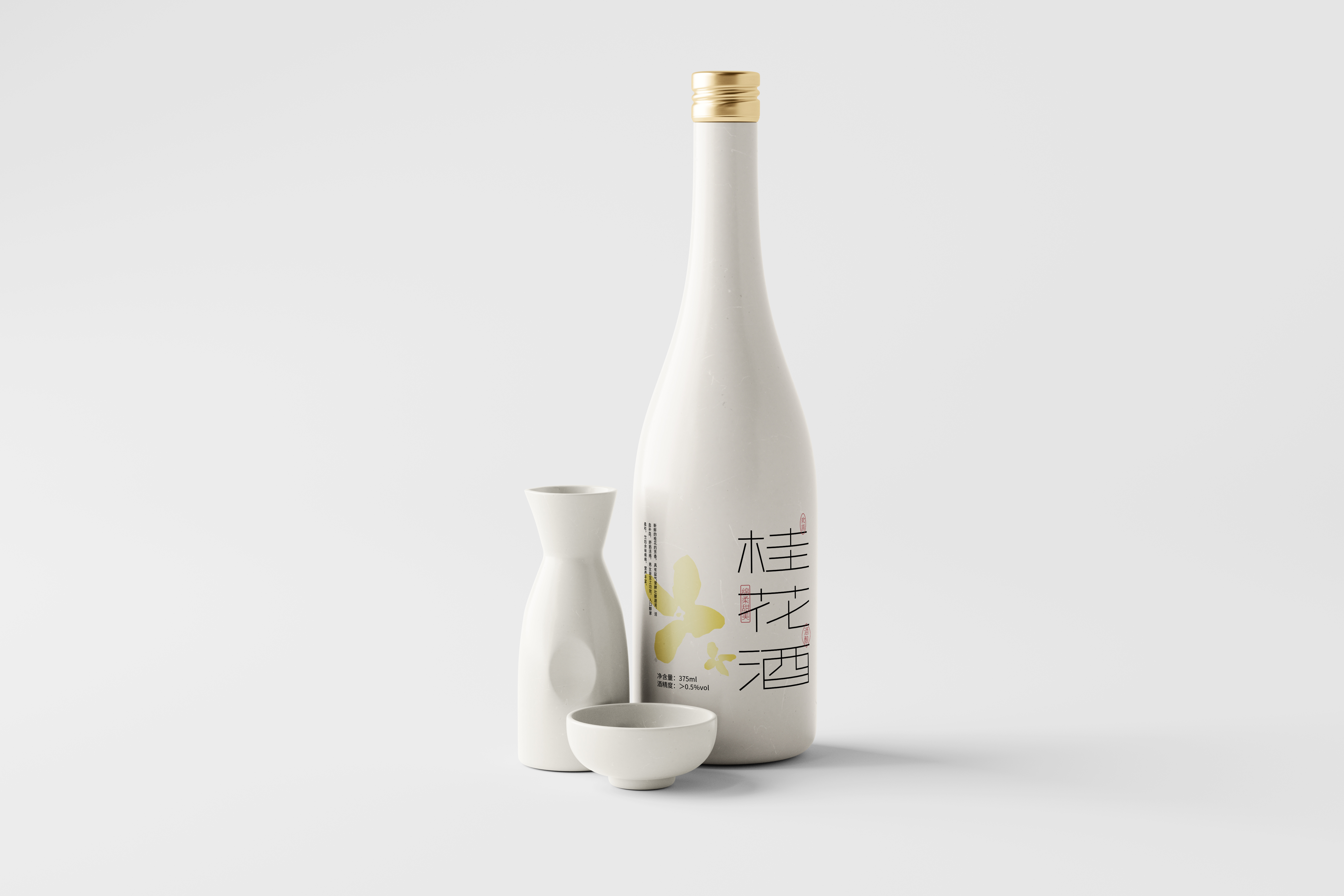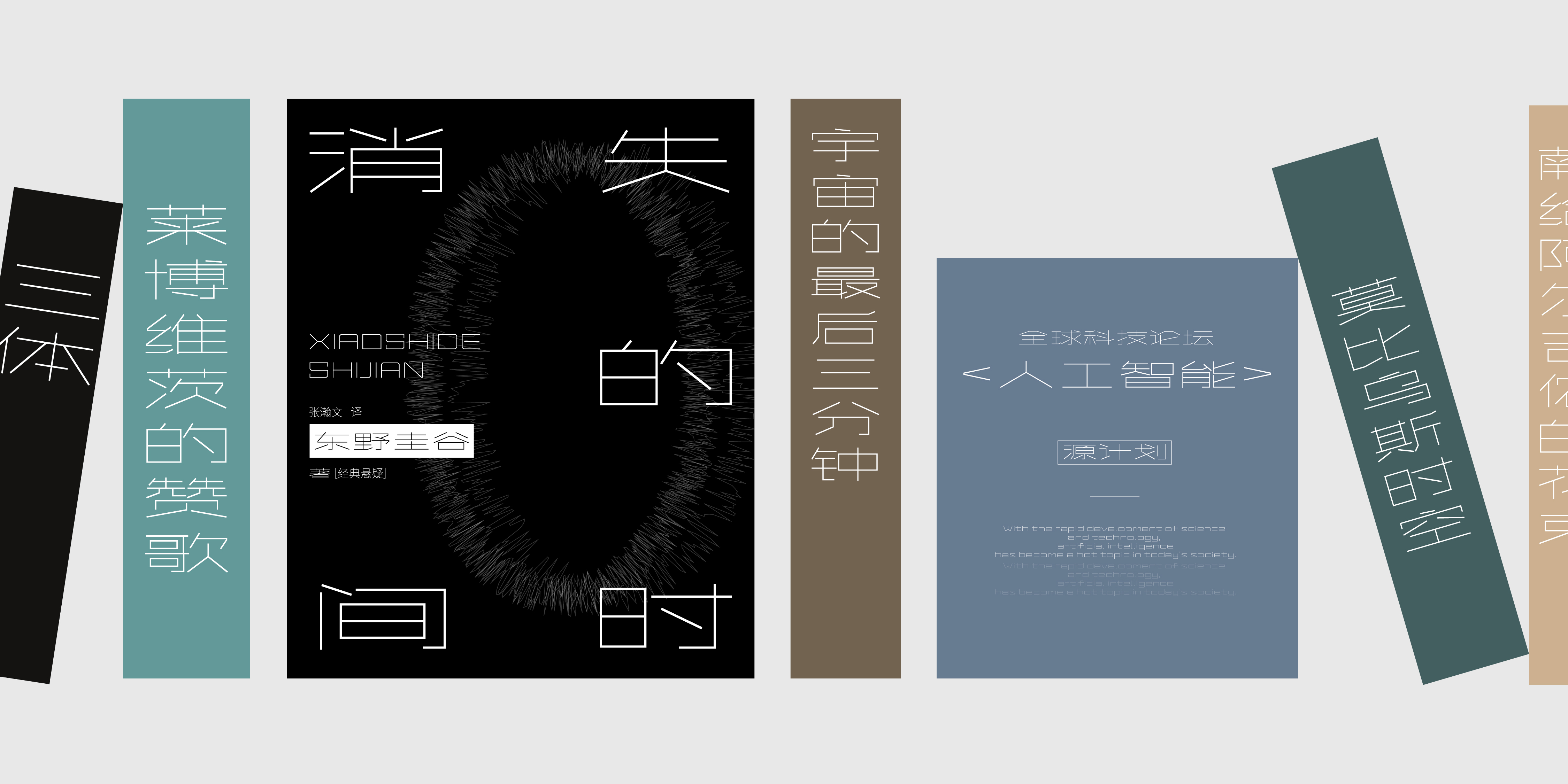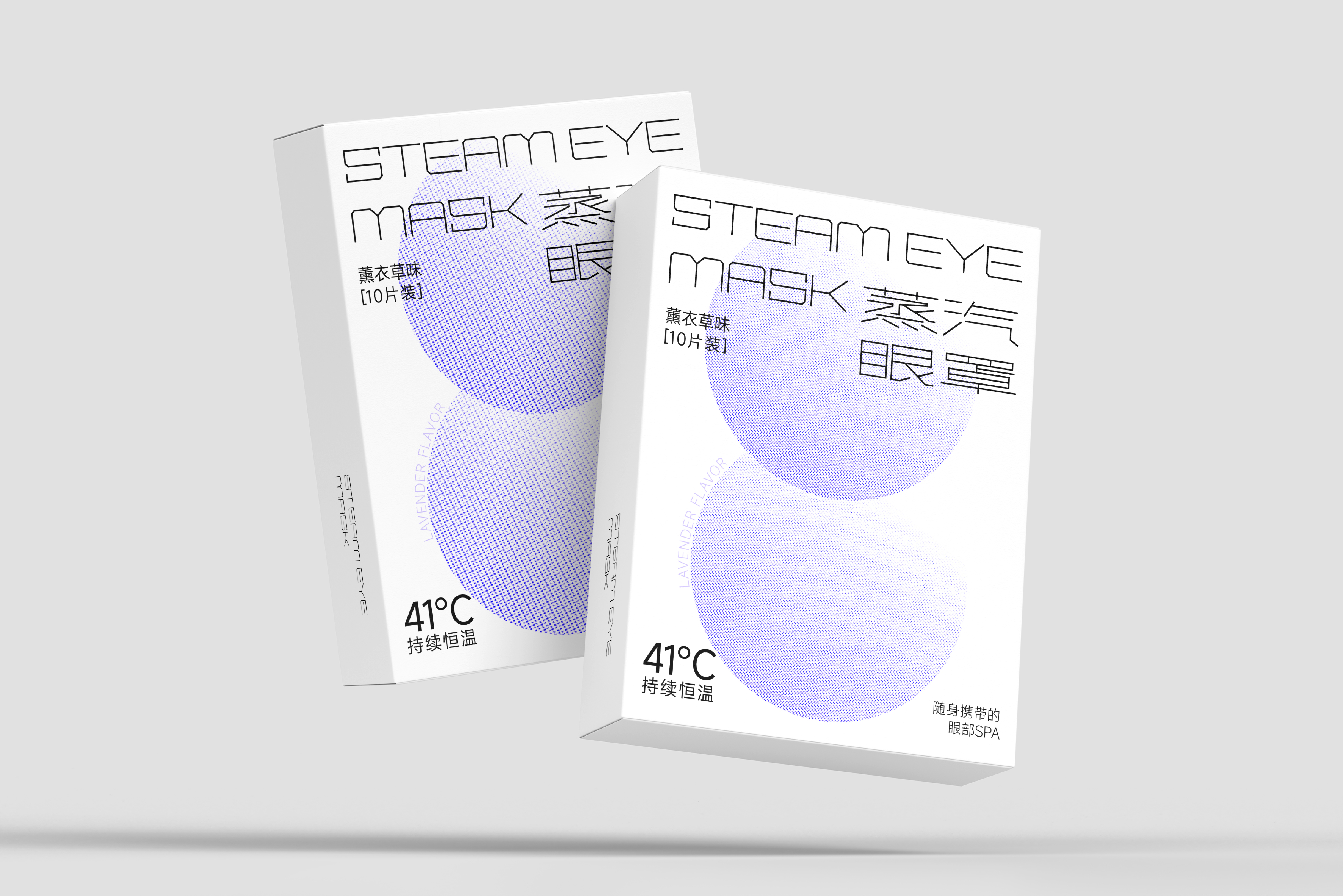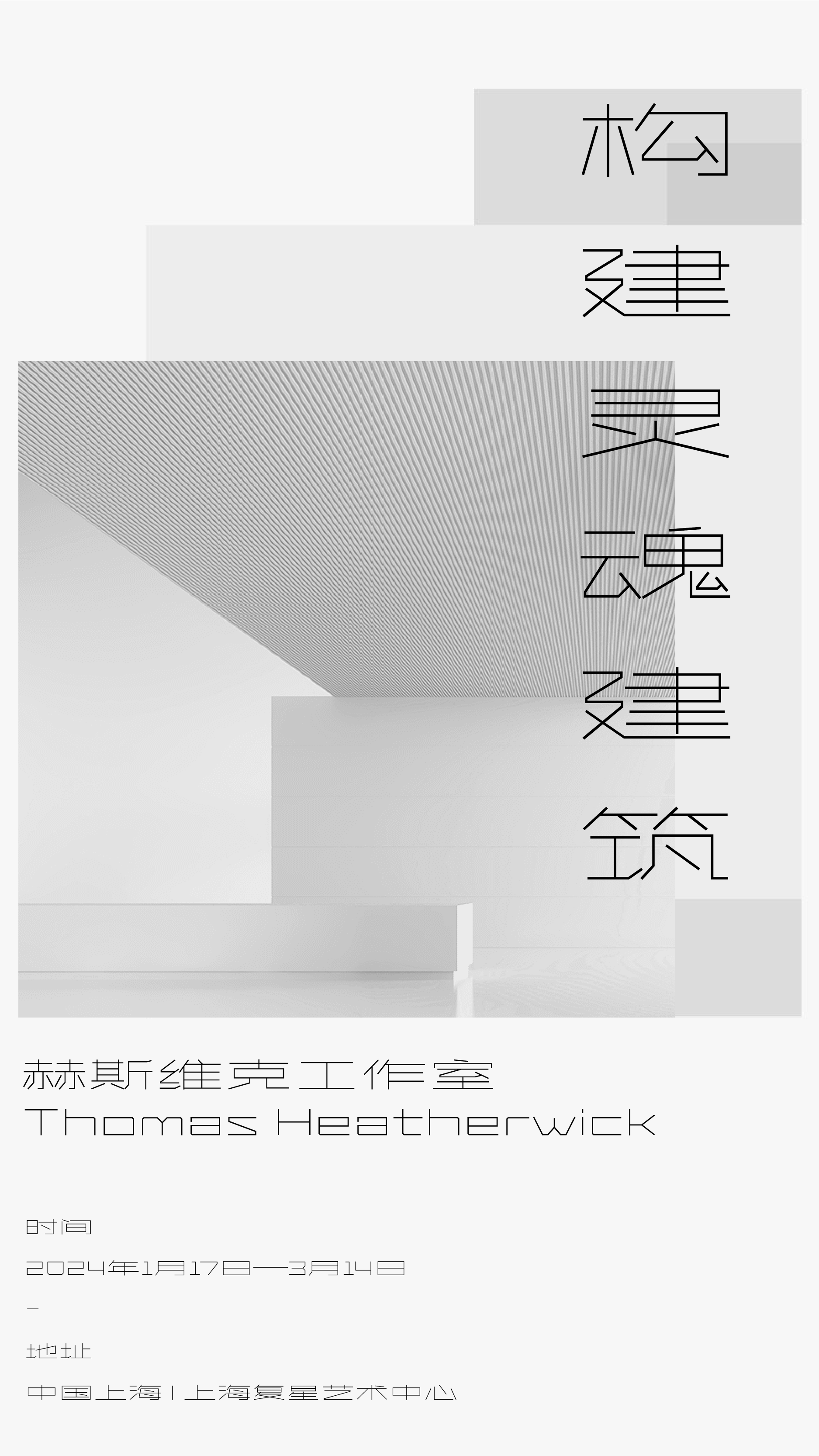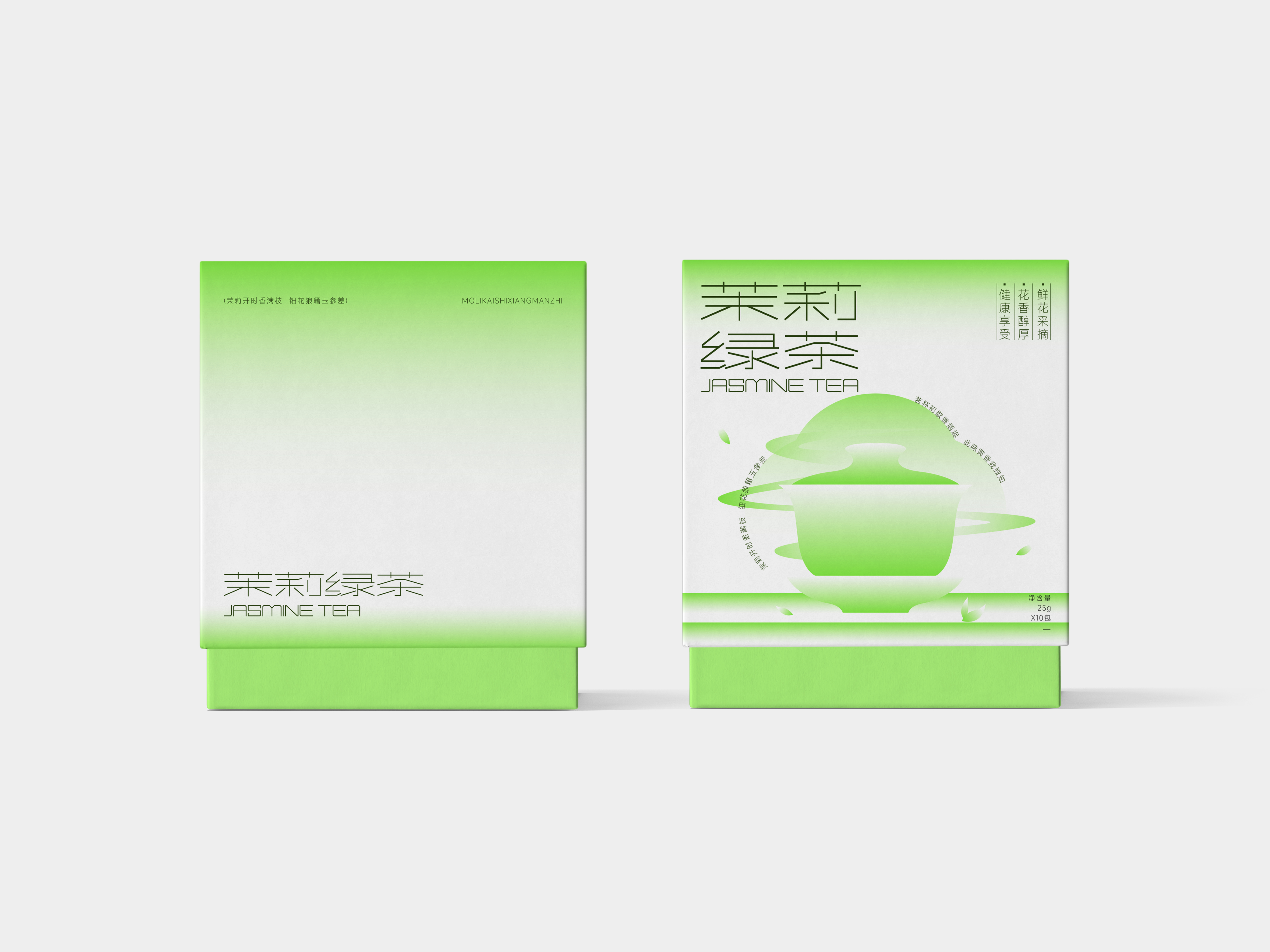
兵克未来体
兵克未来体,兵克未来体,追求极致的简约与纯粹,摒弃了多余的装饰与繁复的笔画,将每一个笔画都精炼到极致,同时以其独特的笔画线条与字面空间的宽窄对比,形成强烈的视觉差,这种视觉差的运用,不仅增强了字体的层次感与立体感,更使得整体设计更加生动、严谨。适用于科技产品、电子产品界面的设计、品牌宣传、广告设计等领域。